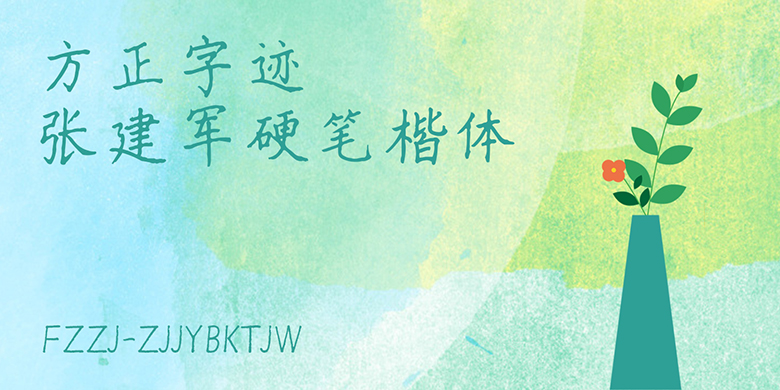
方正字迹-张建军硬笔楷体
方正字迹-张建军硬笔楷体,这款字体结构工整、笔画清晰,兼顾美观与易读性,适用于标题、正文、海报、包装、LOGO 等多种场景。字形优雅稳定,风格百搭耐看,适配日常排版与创意设计,让文字呈现更舒适、更具质感。方正字迹-张建军硬笔楷体一笔一画,皆是细节,以均衡的比例、流畅的线条打造舒适视觉体验,字形端正大气,风格简约现代。无论是商业设计、品牌宣传还是日常排版,都能轻松驾驭,让文字更有格调与力量。方正字迹-张建军硬笔楷体字体下载。
张建军硬笔楷体兼具重心平稳、比例适当、字体端正、刚柔相济、方圆并存等特色,是临习范本。适合习字临帖、字体印刷、文化宣传、商业广告和产品包装设计等。